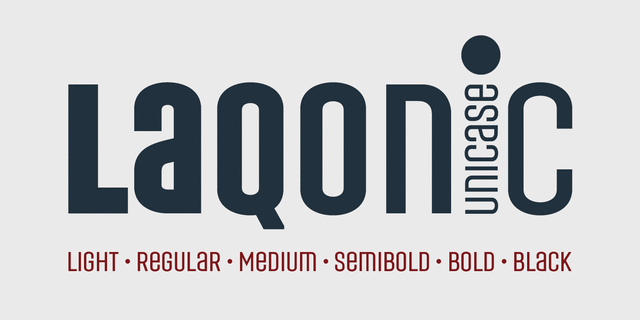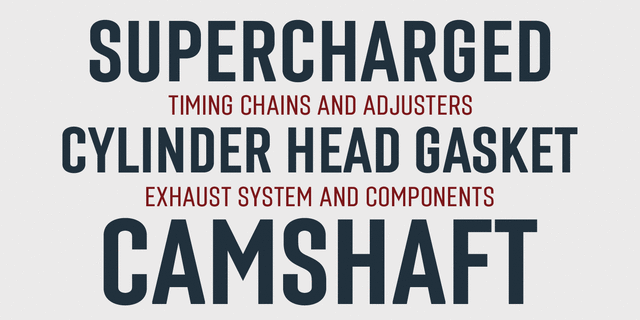
Шрифт Laqonic – геометрический модульный гротеск с технологическим характером, отлично подхоядщий для вывесок, логотипов и громких заголовокв. Разработан в студии 4th february в 2014 году, дизайнер Сергей Ткаченко.
Качества и характер:
точный ,
ровный ,
убедительный ,
прямоугольный ,
стабильный ,
твердый ,
серьезный ,
надежный ,
уверенный ,
сильный ,
устойчивый ,
индустриальный ,
техногенный ,
статичный ,
городской ,
простой ,
автоматический ,
урбанистический ,
стальной ,
крепкий ,
строгий ,
современный ,
монотонный ,
логичный ,
прагматичный ,
практичный ,
искусственный ,
холодный ,
машинный ,
инженерный ,
мотивирующий ,
железный ,
громкий ,
важный ,
стройный ,
высокий ,
дорогой ,
качественный ,
кинематографичный ,
лаконичный ,
чертежный ,
минималистичный ,
техничный ,
гладкий ,
футуристичный ,
спортивный ,
срочный ,
авторитетный ,
амбициозный ,
заметный ,
гордый ,
монументальный ,
мужественный ,
крутой ,
архитектурный ,
ответственный ,
сжатый ,
солидный ,
мощный ,
тяжелый ,
увесистый ,
тесный ,
черный